#1 영국 타이포그래피 기행 London Typography Tour ①
2011년 6월 7일, 오랜만에 화창하고 푸른 샌프란시스코 하늘 위로 날아올라 미대륙을 가로지르며 그렇게 대서양을 넘어 유럽을 향하는 비행기 안에서 나는 호기심 어린 학생들과 이런저런 이야기를 나누고 있었다. 3년 만에 다시 찾는 유럽… 첫 번째 목적지는 런던이었다. 첫 일주일은 현대 타이포그래피 매거진의 진수인 Baseline Magazine, 글꼴 디자인 교육의 메카인 University of Reading, 그리고 최근에 영국에서 가장 영향력 있는 폰트전문 제작회사 중 하나인 Dalton Maag Font Foundry를 방문하여 워크샵을 통하여 학생들에게 영국 타이포그래피의 사적 고찰과 흐름, 그리고 글꼴디자인의 영감을 심어주는 계기가 되길 희망하였다.
워크샵 진행 중간엔 예술 문화 체험의 목적으로 British Museum, Design Museum, Victorian & Albert Museum, Science Museum, Tat Modern, RCA 등을 방문하였다. 늘 그러하듯이 여행지 도처에 생활 속에서의 디자인과 타이포그래피의 발견은 항상 설레임을 동반한 즐거움이다.
공항 입국 심사장에서부터 대하는 다소 거센 브리티쉬 악센트가 미국 학생들에겐 오히려 묘한 뉘앙스로 다가오며 그렇게 런던에서의 여정은 시작되었다. 300년이 채 안 되는 짧은 역사의 미국은 다국적 이민자들의 사회구조 속에서 의례적으로 자신을 스스로 세계의 리더라고 자부하는 공교육을 하여왔다. 그렇게 성장해 온 젊은 대학생들에 미국 타이포그래피의 원류를 찾아 유럽을 살펴본다는 설렘이 그들의 시야에 들어오는 모든 것에 색다른 의미로 다가왔을 것임을 믿어 의심치 않는다. 5천년 역사의 배경을 가진 한국인 교수로서 내가 미처 느끼지 못하는 미국인들에겐 유럽 문화에 대한 자격지심 같은 것이 기본적으로 잠재해 있음을 오래 전부터 느끼고 있었던 터라 이번 여행은 학생들에겐 더욱더 의미 있는 일이었을 것이다.
2000년과 2006년에 영국을 방문했을 때보다도 이번 여행 중에 런던은 상당히 그 원류적 힘이 차츰 퇴색해 가고 있다는 느낌을 왠지 모르게 받았다. 왜일까? 글로벌 시대가 눈에 보이거나 잠재해 있는 문화를 희석했을 탓일까? 아니면 경제 침체의 파도에 넘실대며 방향을 잃고 표류하는 탓일까? 그것도 아니면 전 세계가 하나가 된 가상현실의 공 간에서 사는 우리 모두의 무국적 이미지의 단편적인 현상이 초래한 결과인가? 하여튼 이제 세계 어디를 가더라도 그 나라만이 가진 유일무이한 예술정신과 스타일이 딱히 뭐라고 정의하거나 쉽게 찾아 보기란 여간 어려운 세상에 우리는 살고 있다. 그래도 세월의 무게 속에 겹겹이 쌓여있는 그 견고한 문화의 후광을 오늘날 우리가 알게 모르게 혜택을 누리고 있다는 사실과 앞으로의 발전 가능성의 무한한 잠재력이 내재해 있다고 확신하면서 이제 영국 타이포그래피 기행 이야기를 시작하고자 한다.
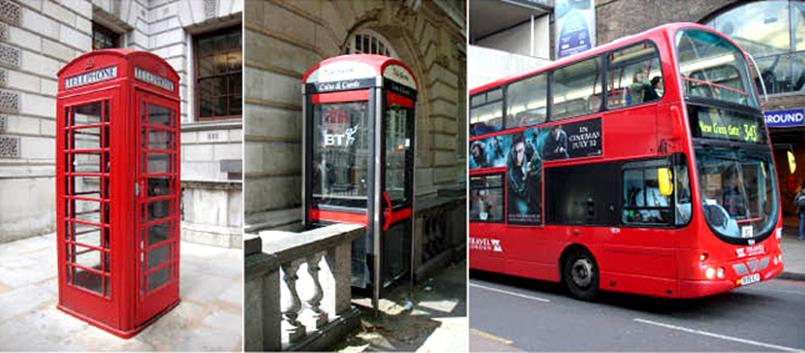
▲ 영국 하면 누구에게나 항상 떠올려지는 이미지들이 있다. 빨간색 2층 버스와 공중전화부스, 그리고 영국황실을 모티브로 각종 국가기업을 중심으로 한 브랜드가 그것이다. 위의 사진에서 보듯이 아직도 런던 시내에선 초기 디자인의 공중전화부스가 최근 리디자인 된 것과 혼용되어 쓰이고 있다. 2층 버스도 여러가지 디자인으로 발전되어 오고 있다.
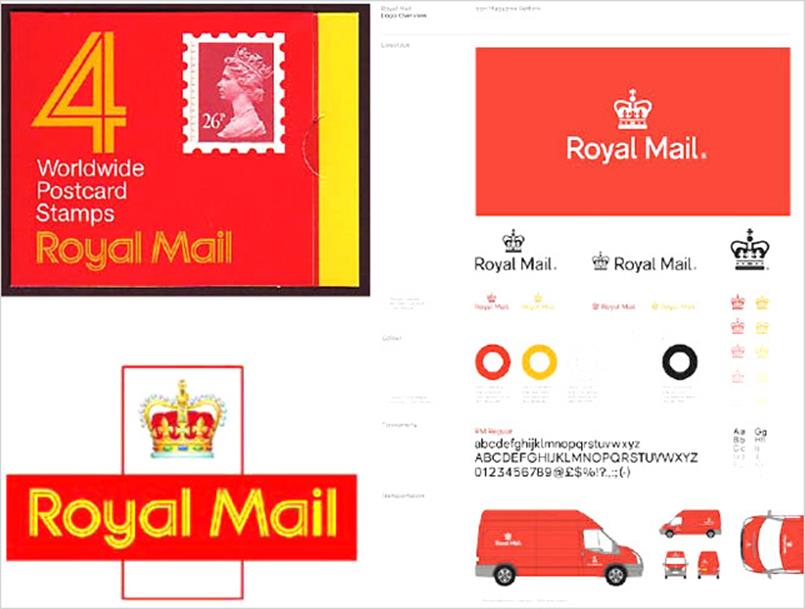
▲ Royal Mail은 그 이름과 소재에서 풍기는 고풍스러운 이미지를 드러내고자 간략하고 강렬한 컨셉트와 색상으로 디자인되었다. 오른쪽 애플리케이션에서 볼 수 있듯이 어떻게 장식적인 모티브가 이렇게 간결한 레이아웃에 적용되어 커뮤니케이션을 극대화하는가를 보여주는 단적인 예이다. 우리의 우체국 사인이나 그래픽 모티브와 사뭇 비교된다.
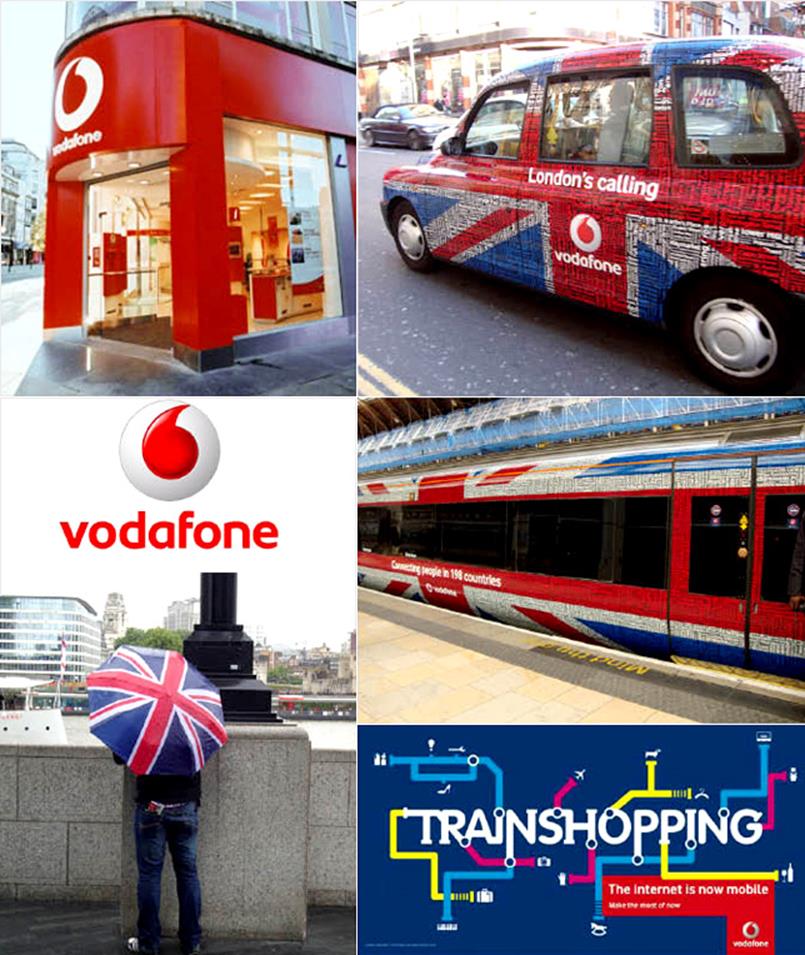
▲ 위의 사진들은 최근 런던 시내에서 흔히 볼 수 있는 광고물 중에 이동통신 서비스회사인 Vodafone의 지점과 택시와 전철 등 교통수단에 적용된 그래픽(영국 국기와 타이포그래피를 잘 활용한 광고)과 로고이다. 우측하단의 사진은 BBH London 광고 대행사가 제작한 모바일 인터넷 서비스를 알리는 광고물로 유명한 런던 서브웨이 노선도의 시각적 특성을 연상시키는 컨셉이다.
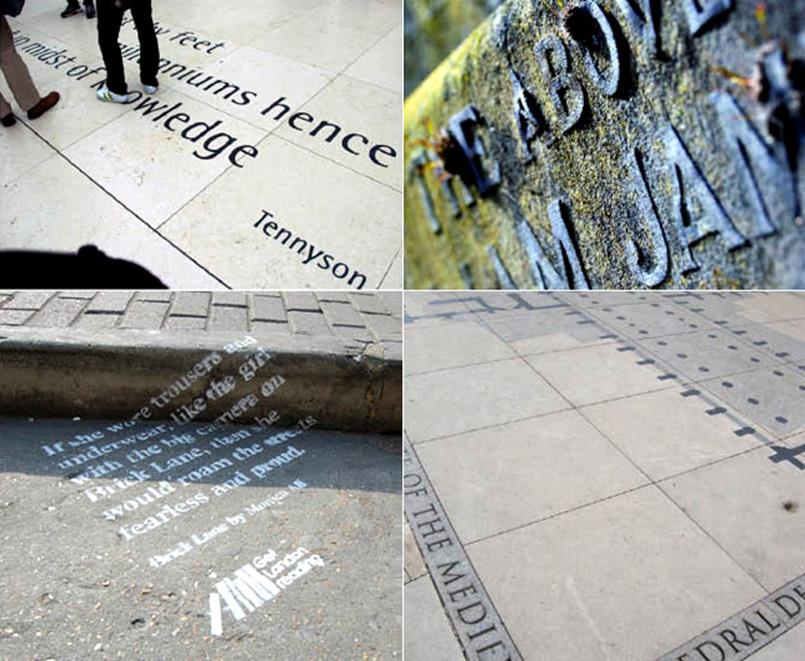
▲ 우리의 삶과 생활 속에 자리하고 있는 각종 환경 타이포그래피의 예들. 문자는 우리의 말과 생각과 소통을 위하여 그렇게 늘 우리 곁에 존재해 왔고 사람들은 이러한 기호를 통한 논리적인 놀이와 상호교류를 즐겨왔으며 나아가 역사의 중 심에 기록으로 남아 후세에게 선조의 영광을 찬미하여 새로운 도약의 발판으로 자극하는 매개물로 살아 숨 쉰다. 그래서 우리는 타이포그래피에 그렇게 열광하는 이유인지도 모르겠다.
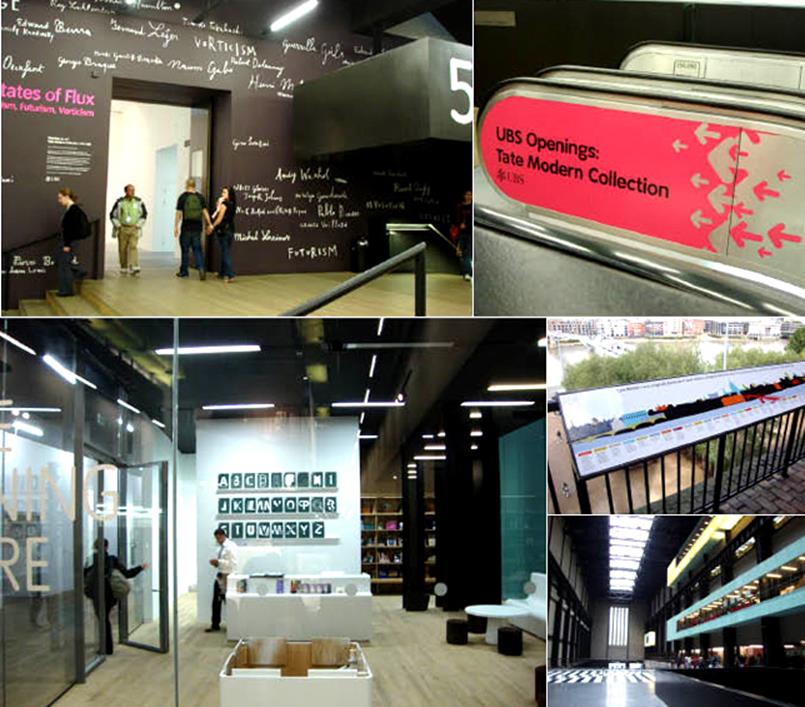
▲ 위의 사진은 Tat Modern gallery 내부의 전시장으로 진입하는 공간의 타이포그래피로, 설치 작업과 에스컬레이터에 방향을 지시하는 정보이며 동시에 장식적인 그래픽 모티브로서의 타이포그래피 적용 예이다. 좌측 아래의 사진은 지하 전시장과 갤러리 스토어로 연결되는 부분에 위치한 미술관련 교육 세미나실의 전경이다. 알파벳을 이용한 흥미로운 벽면 구성이 돋보인다.
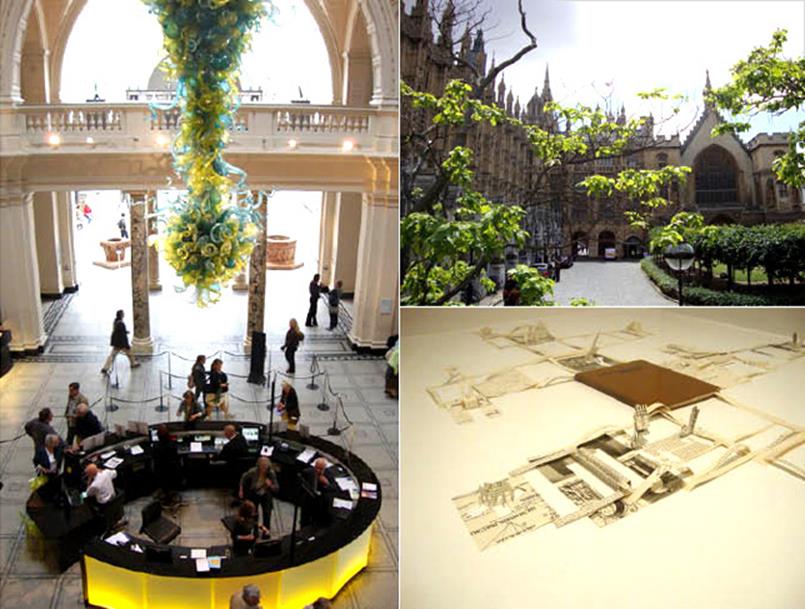
▲ Victorian & Albert Museum 내부 전경 고전과 현대의 조화가 돋보이는 박물관으로 다방면에 흥미로운 특별 전시가 매월 기획된다. 우측 하단의 사진은 건축관련 전시에 디스플레이 되었던 다이컷으로 구성된 건축 서적이다. 흥미로운 것은 기존의 pop up book이 갖고 있는 도형의 입체화에 그치지 않고 타이포그래피와 각 펼침 페이지, 그리고 건축물 드로잉이 한데 어울려서 마치 거대한 도심의 파노라마 모형도를 연상시킨다는 것이다.
이번에 영국 (특별히 런던)을 기행하며 “영국 타이포그래피”에 대하여 되돌아 보는 시간을 갖게 되었다. 그때 먼저 떠오른 것이 독일과 이탈리아 그리고 프랑스와 연계된 “중세 납활자와 인쇄술”, 그리고 서체디자인의 대중화가 발전 되었는가? 였다. 나아가 18세기 빅토리안 미술의”공예운동”(나중에 근대 디자인의 모태가 되는)에 미친 영향과 19세기 말 산업혁명의 태동과 그 후 폭풍인 1, 2차 세계대전의 흐름을 되짚어 봐야 한다는 생각이 문득 들었다.
본 칼럼의 성격에 기초하여 영국의 근현대 서체디자인과 타이포그래피 역사를 간략히 되짚어 보자. 아는 바와 같이 15세기 전까지는 주로 커뮤니케이션과 기록의 수단으로 이른바 필사본 (manuscript; 거의 글을 그린다는 개념에 가까운 수작업 출판)이 그 주류를 이루었다. 15 세기에 이르러서야 납활자를 조판해 재활용할 수 있는 기계화 복제 시스템이 가능해 졌다.
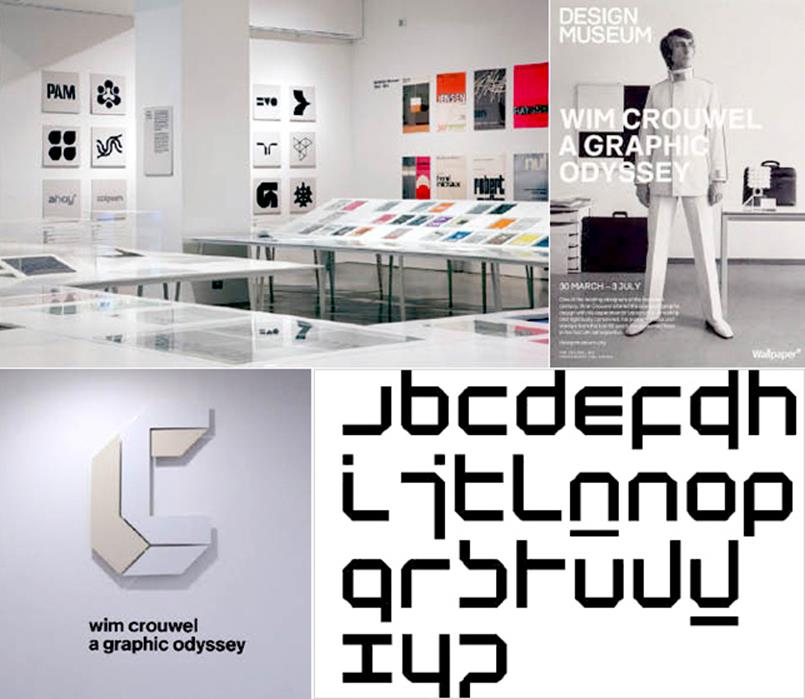
▲ 네덜란드를 대표하는 타이포그래퍼이자 그래픽 디자이너인 Wim Crouwel의 작품을 총망라한 대형 전시 “a graphic odyssey”가 지난 6월 런던 여행 중 London design museum에서 있었다. 윗줄의 사진은 전시장 내부 전경과 포스터이다. 아래는 그의 디자인 스타일과 철학을 잘 드러내는 전시 엠블렘이며 우측은 이른바, new typography로 명명된 미래주의적 서체 구조를 가진 그의 유명한 디자인이다. 이 작품은 후에 세계 각국의 디자이너들에게 엄청난 영향을 주었고 우리나라에서도 그 영향을 받은 글꼴들이 만들어졌다.
▲ 좌측의 위로부터 Baskerville, Caslon, Didot, Gill Sans, 그리고 Matthew Carter가 리디자인 한 Big Caslon 서체이다. 획과 카운터 스페이스 그리고 중심축의 각도가 변화되어온 이른바 과도기적 현상을 살펴볼 수 있다. 오른쪽 사진은 런던 시내 한 성당에서 흔히 볼 수 있는 서체와 애플리케이션이다.
▲ Caslon체의 서체 견본과 Chiswell Street에 있던 활자공방의 내부 모습
평소에 책 출판에 관심이 많았던 영국인 William Caxton은 15세기 말 유럽 전역을 여행하며 자료를 수집하고 급기야 영국 Westminster로 돌아와 본격적으로 인쇄소를 설립하고 출판사업을 시작하였다. 그래픽 디자인 역사의 중심에 서기에는 다소 전문성이 부족했던 타입세터이자 출판인이었지만, 근대 영국 타이포그래피와 인쇄분야에 선구자적 역할을 하였다는데 큰 의미가 있다. Incunabula (1450s to 1500년)로 불리는 기간 동안은 아직도 필사본(manuscript)이 서적출판에 주류를 이루고 있었고 납활자를 이용한 근대 타이포그래피 시대로 접어들면서 William Caxton은 이른바 colophon이라는 독특한 형식을 만들어 냈다. 인쇄소와 출판 제작 관련 정보를 기록하는 섹션: 인쇄소 정보, 인쇄공 이름, 사용 활자, 종이, 인쇄, 제본방식 이외에 책 내용이 아닌 출판 프로덕션에 관한 저작권에 대한 보호를 위한 방식으로서 사용되기도 하였다. 최근에 거의 모든 서적에 뒷부분에 찾아볼 수 있는 하나의 포맷이 되었다.
Incunabula 시기가 거의 끝나갈 무렵 colophon 구조는 책의 서두에 등장하는 half title(나중에 title page로 확장되는)에 그 일부 기능(저자 및 출판사의 이름 등)이 옮겨져 왔다. 흥미로운 것은 필사본 시대까지만 해도 책의 저자에 대한 정보가 드러나지 않았다는 사실이다.
18세기 초엽(1734)에 마침내 글자 구성과 활용에 관한 가이드라인이 되는 최초의 근대적 개념의 type-specimen이 등장하게 되는데, Garamond style의 Aldine roman 서체를 근간으로 좀 더 다듬은 서체(Caslon)를 만든 William Caslon이 바로 그 장본인이었다. 이 서체는 절도 있는 느낌의 클래식 스타일이며 약간의 가늘고 굵은 획들 간의 대조가 돋보이는 글꼴이었다. 나중에 Caslon체는 Benjamin Franklin을 통하여 미국에 소개되었고 Baltimore 에 있는 인쇄소를 동하여 공식적으로 미국독립선언문(United States Declaration of Independence)의 복제본을 만드는데 사용되면서 대중적인 글꼴이 되기도 하였다.
Kelmscott Press에서1896년에 출간한 책인 Chaucer은 독일의 출판물 디자인에서 크게 영향을 받은 이른바 보고 즐기는 감상용 책으로서의 전형을 보여준다. 후에 이에 영향을 받은 대표적인 영국출판사가 Doves와 Ashendene presses이다. 1900년에 창립된 Doves press는 T.J. Cobden-Sanderson와 Emery Walker에 의해 아르누보 스타일의 장식미학과 간결하고 완벽한 공예미의 조화를 이루어낸 성공적인 예이다. 20세기 초반에 더욱 더 기계화 산업화가 가속되는 와중에 출판 분야에서는 여전히 전통적인 글꼴 (Caslon)을 기초로 한 대량 생산용 활자가 대중적으로 주조되기 시작하였고 이와 더불어 독일을 중심으로 sans serif체가 세상에 선보이게 되었다. 미술과 문학 전반에 새로운 사조(다다이즘, 미래파, 큐비즘, 구성주의 등)가 등장하면서 전통적인 타이포그래피와 실험적인 타이포그래피의 혼재가 거듭되었고 이는 서로 반발과 융합이라는 자연의 법칙을 통하여 여러 갈래로 발전되어 갔다.